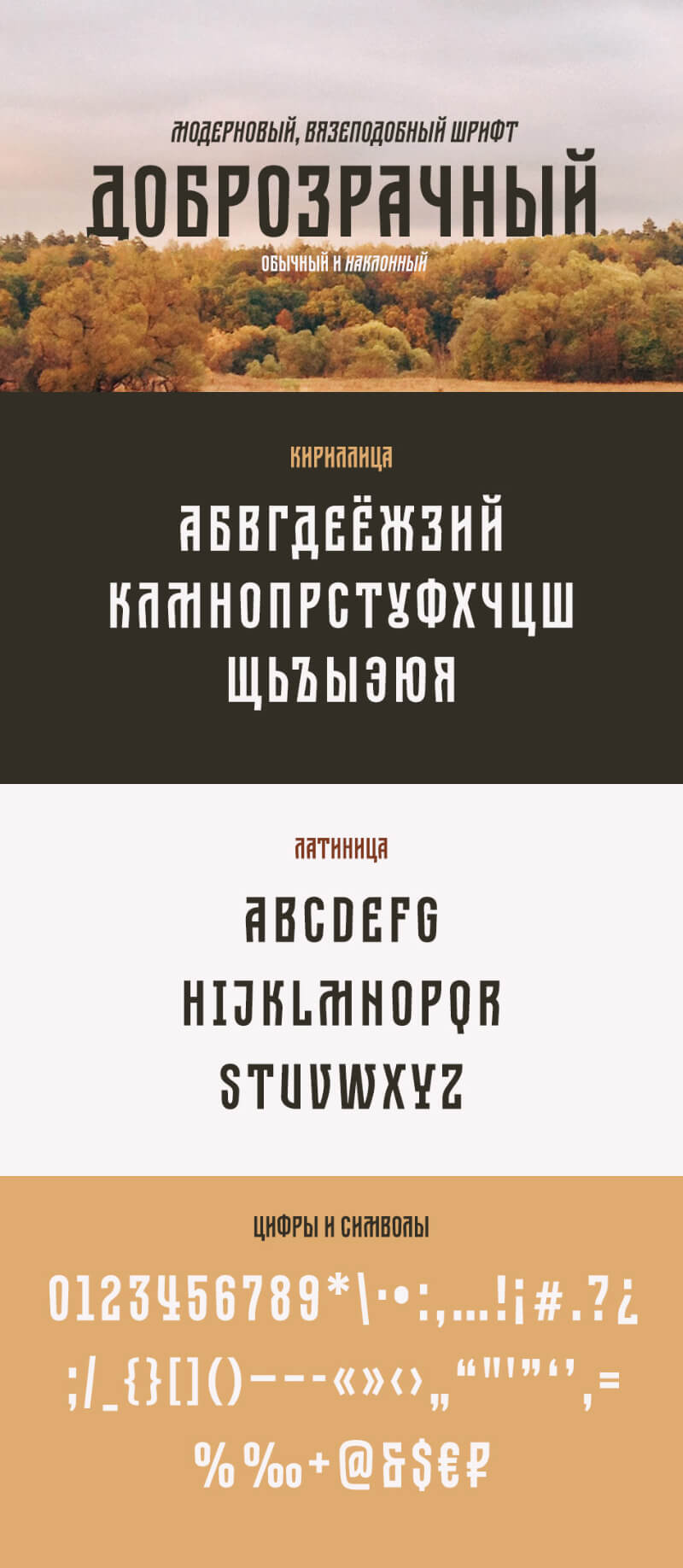
Шрифт - Доброзрачный
Дизайн этого шрифта создан на основе допетровской кириллицы и стилизованный под модерн. Два начертания: обычное и наклонное. Подойдёт для заголовков и небольших объёмов текста, логотипов и иллюстраций, плакатов и упаковки.